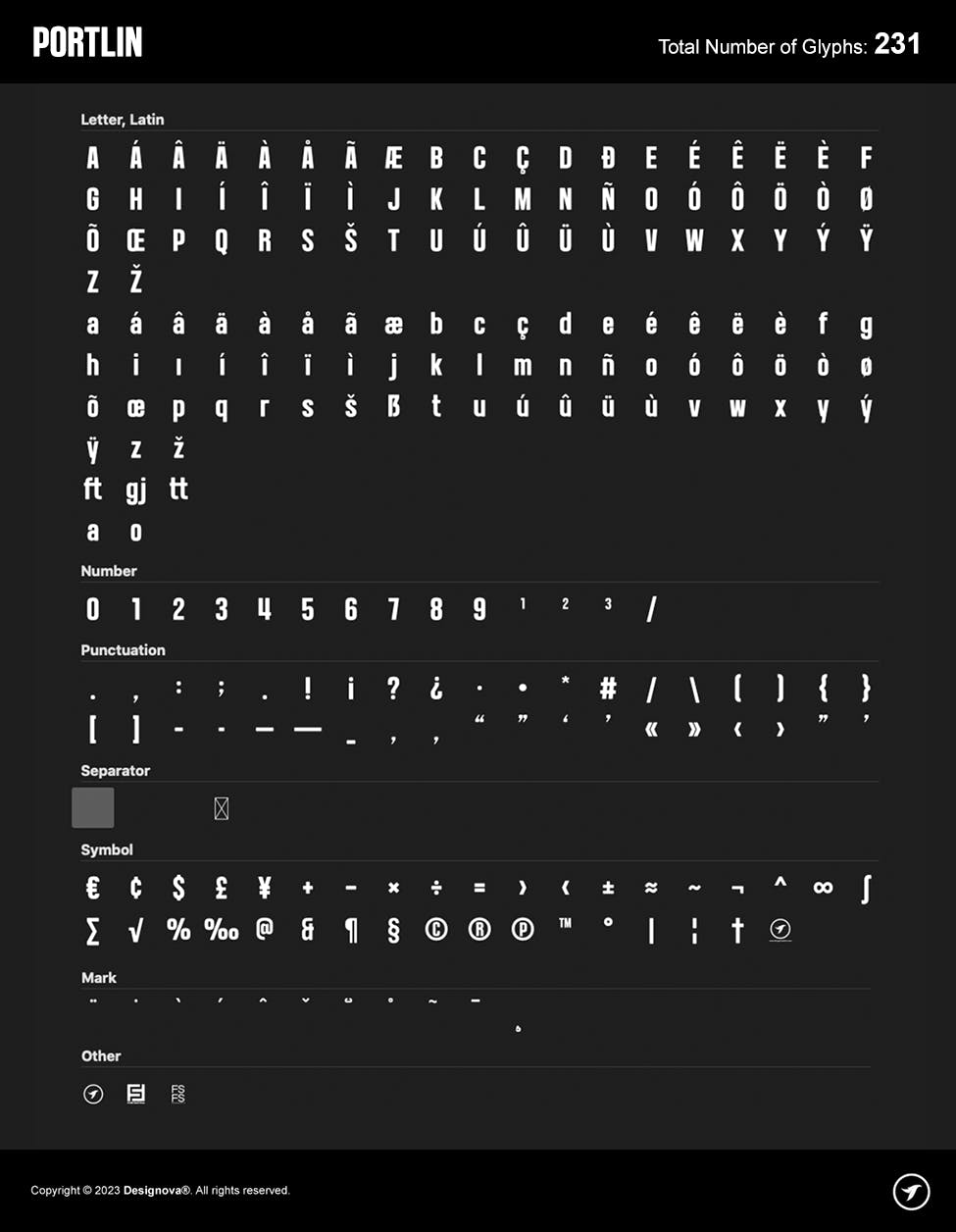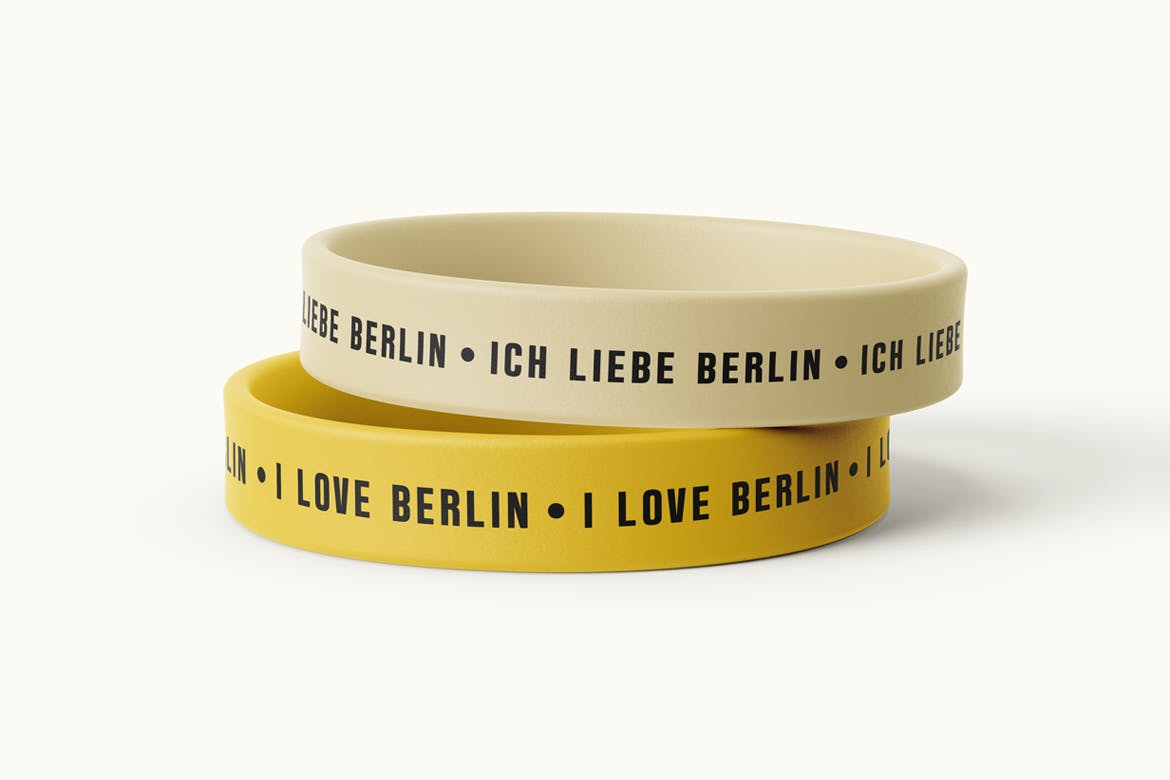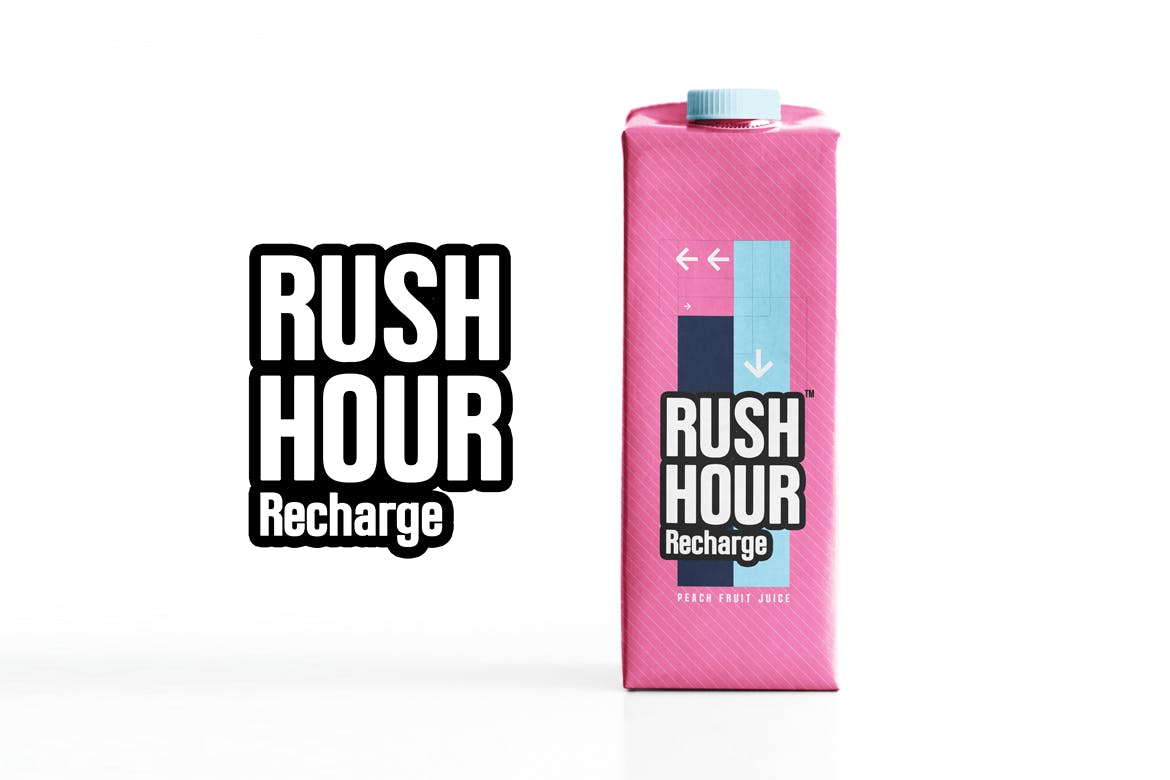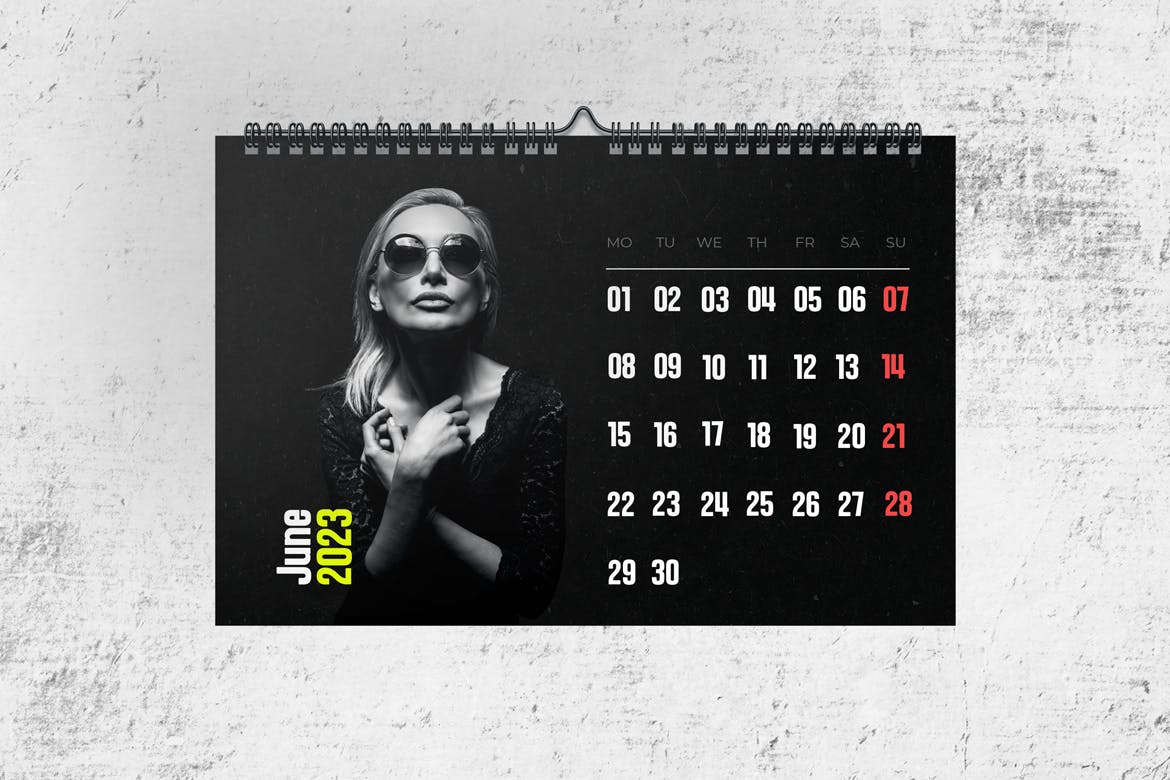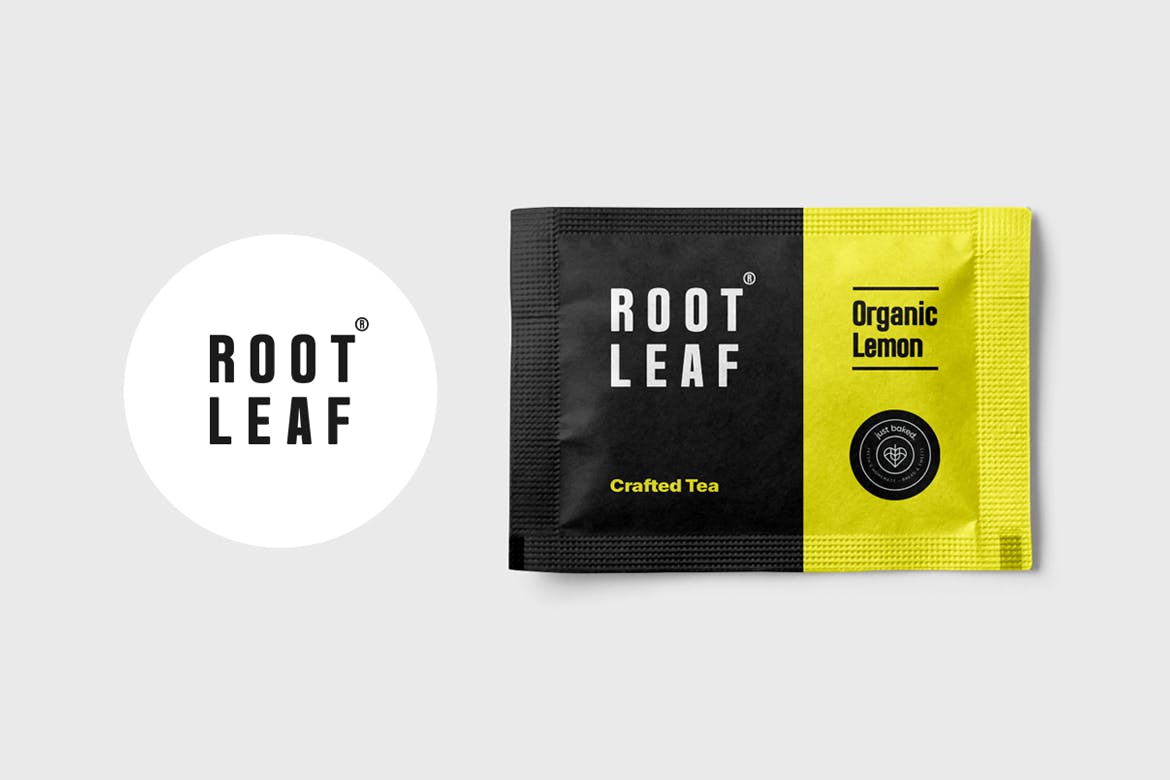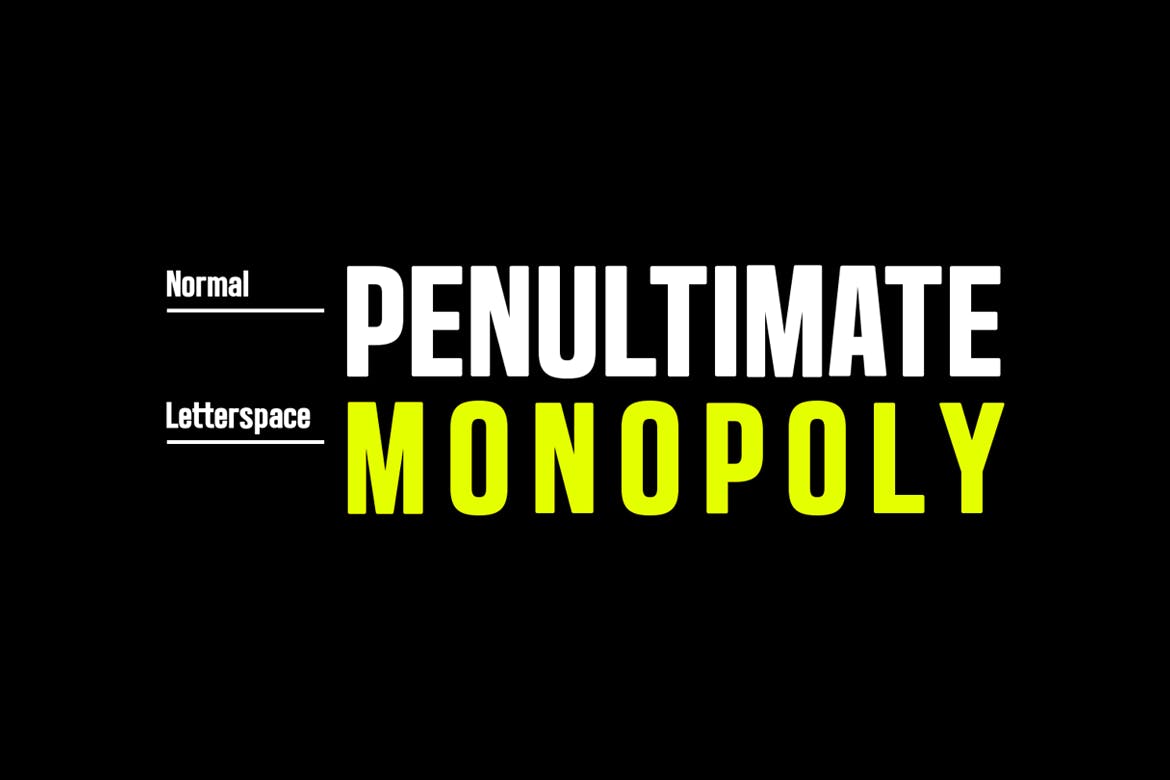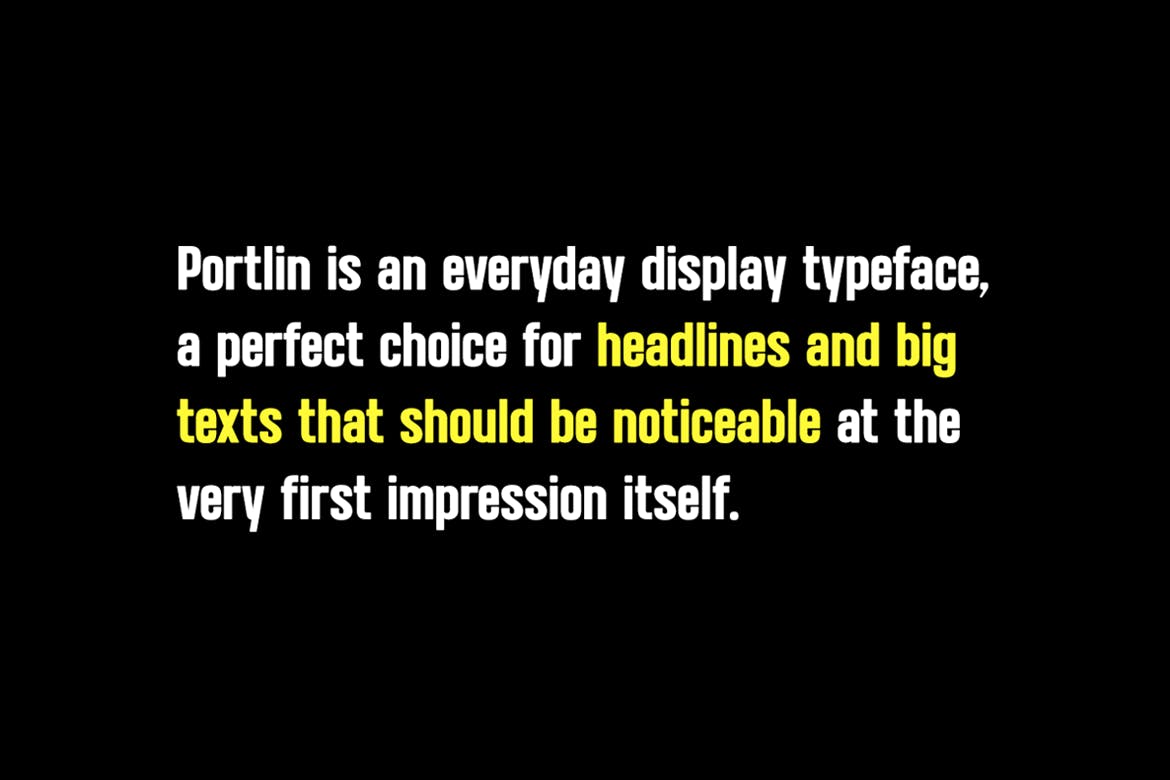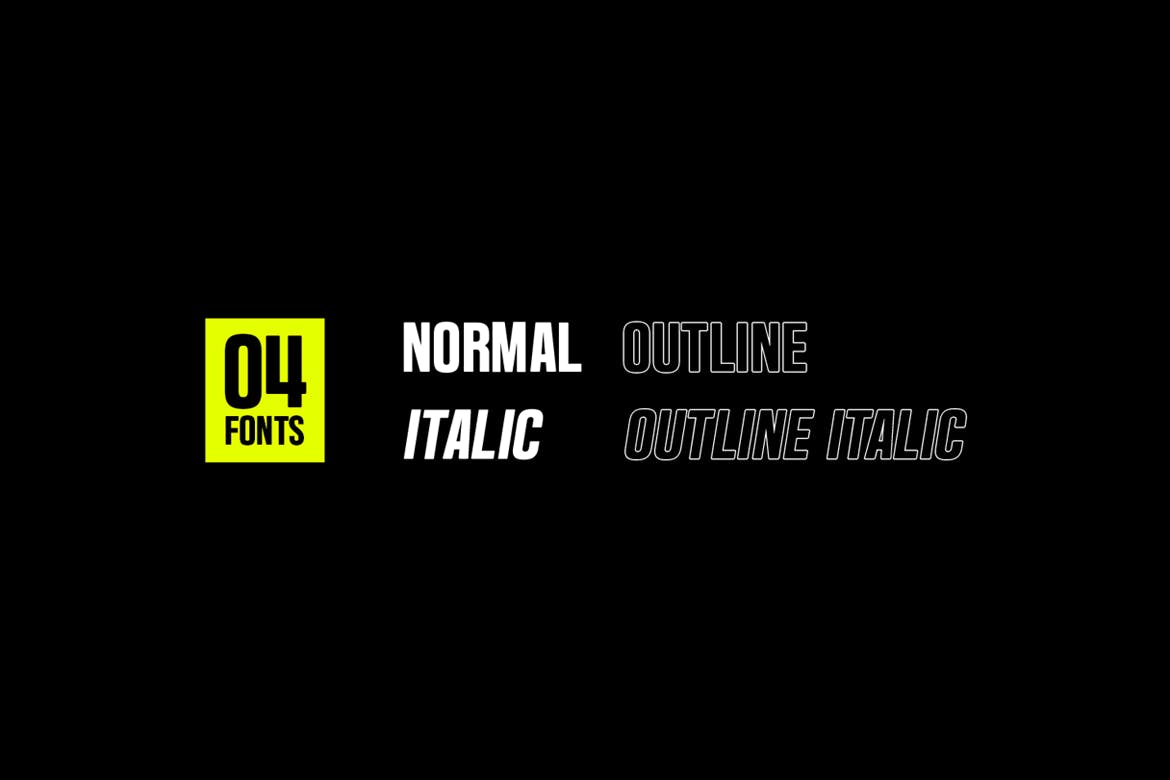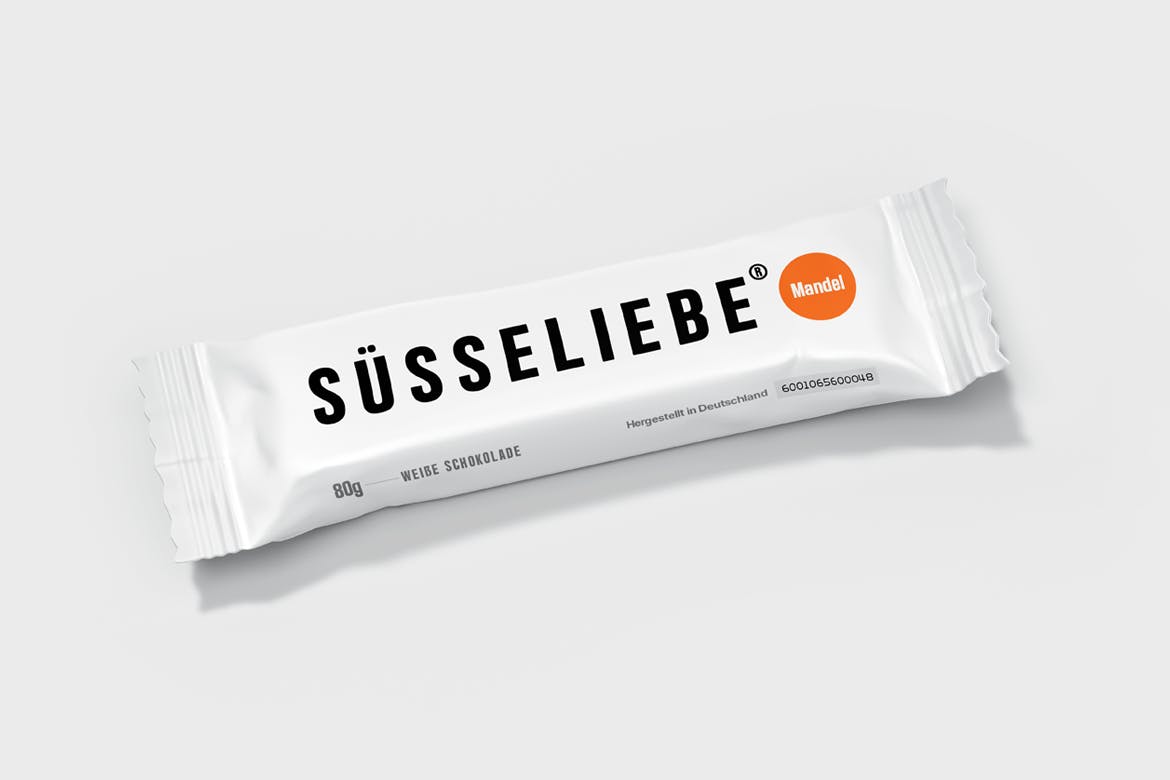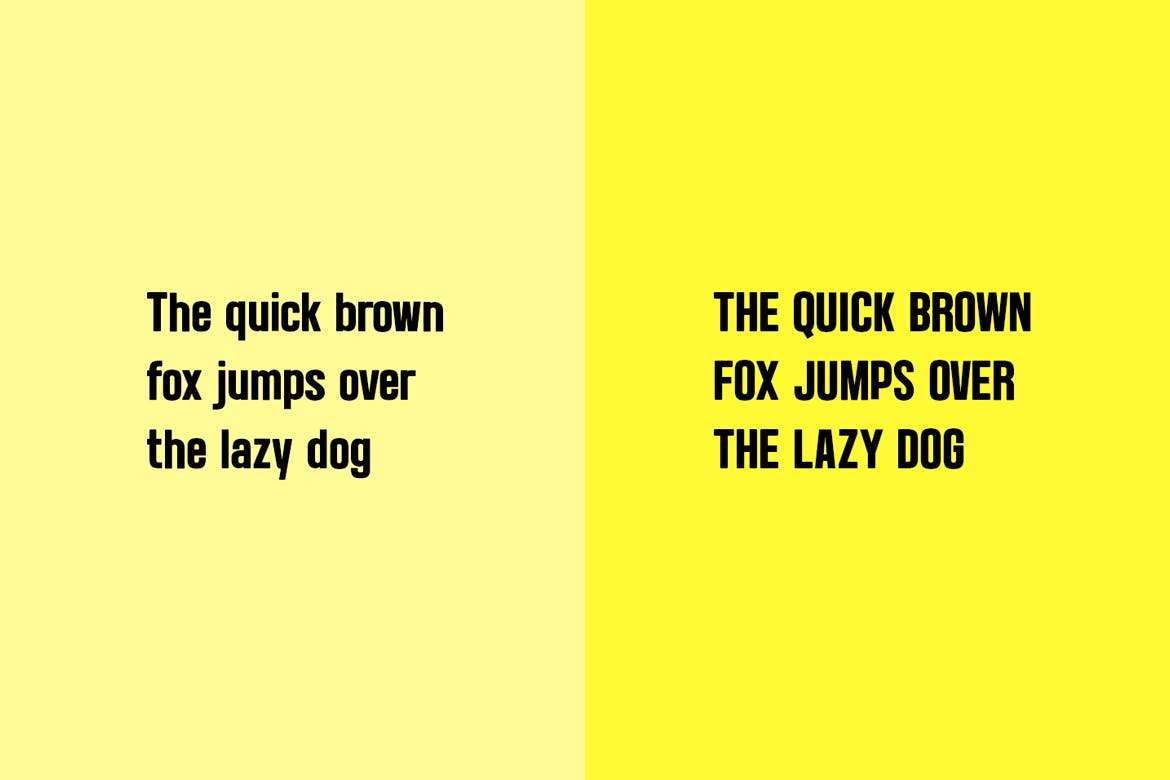
فونت Portlin، یک نوعخط مدرن و جذاب است که برای تیترها، متنهای بزرگ، برندینگ، لوگوتایپها و مقاصد طراحی گرافیکی مانند پوسترها، بروشورها و تبلیغات مناسب میباشد.
این فونت گزینهای عالی برای خلق لوگوهای منحصر به فرد، محتوای تبلیغاتی و ارائههای بازاریابی است که میتواند طراوت و تازگی را به پروژههای شما بیاورد.
فونت Portlin از نظر خلاقیت بسیار انعطافپذیر است و شما میتوانید فاصله حروف را تنظیم کنید تا ارائههای متنی خاصی طراحی کنید، بهویژه برای ایجاد لوگوتایپها و طراحیهای برندینگ شگفتانگیز. لطفاً به نمونههای ارائهشده در بالا نگاهی بیندازید تا با قابلیتهای این نوعخط آشنا شوید.
فونت Portlin دارای پشتیبانی از زبانهای مختلف است که شامل مجموعه کاراکترهای اروپای غربی، اروپای مرکزی و اروپای جنوب شرقی میباشد (در مجموع ۲۳۱ گلیف).
خانواده فونت Portlin شامل ۴ فونت (معمولی / ایتالیک / حاشیهدار / حاشیهدار ایتالیک) است. این بسته شامل فرمتهای OTF و TTF بهعنوان فونتهای دسکتاپ و فونتهای وب اختیاری (شامل تمام فرمتهای EOT، SVG، TTF، WOFF و WOFF2) میباشد.
این نوعخط توسط Designova طراحی شده است.